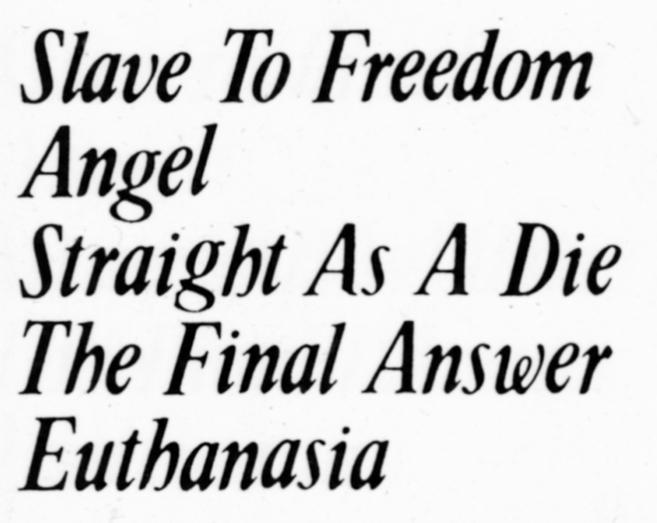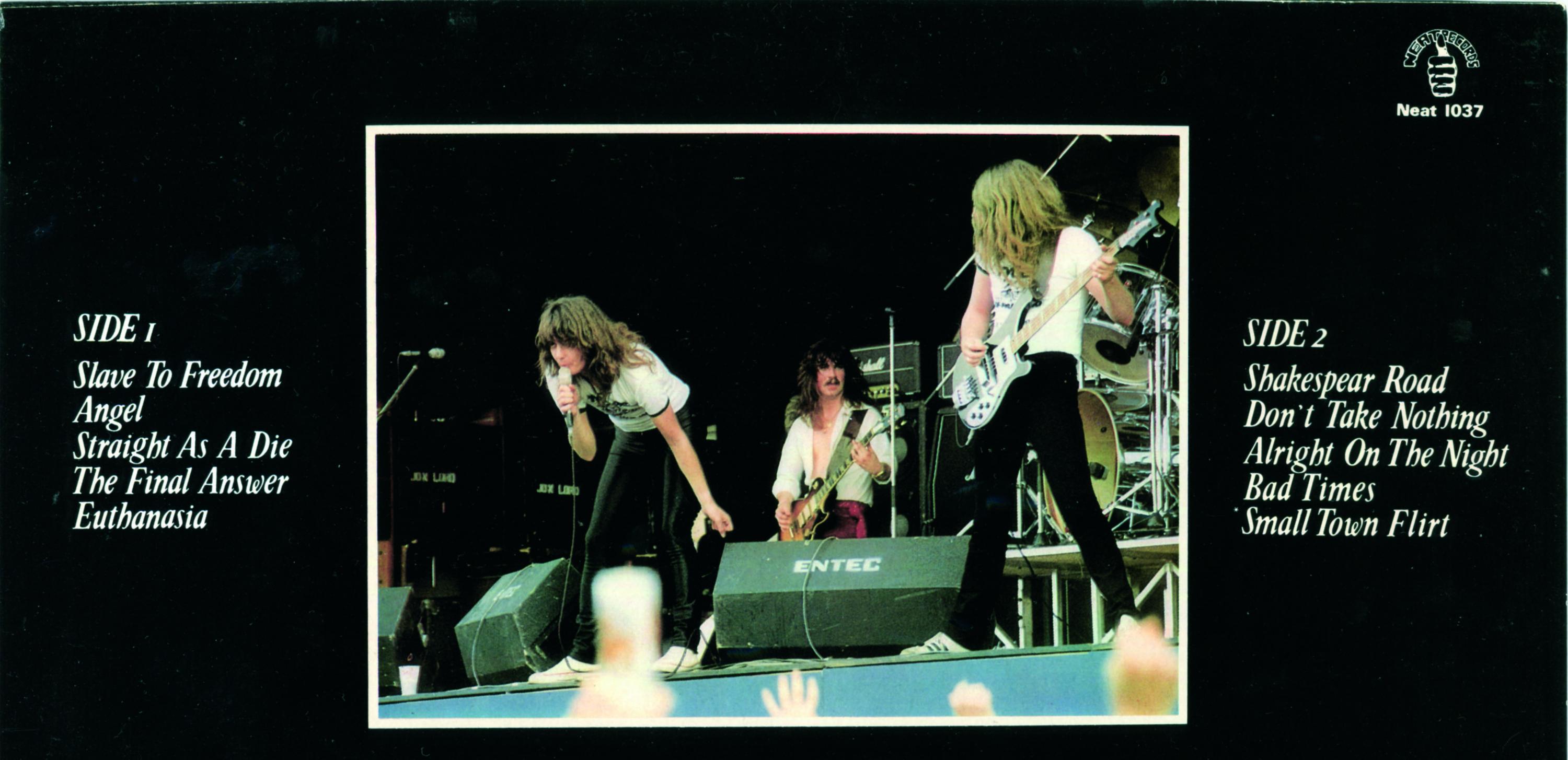
Suche 2 Schriften für ein Vinyl-Rerelease (Tygers of Pan Tang)
Für ein offizielles Vinylrelease suche ich 2 Fonts. Das Original erschien 1986.
Ich dachte, es wären die Baskerville und die Zapf Chancery. Leider sind sie nur ähnlich.
konkrete Angaben zum Originalrelease:
Titel: First Kill
Band: Tygers of Pan Tang
Jahr: 1986
Label: Neat Records (Europe)
die Anhänge sind Scans des Originalreleases
"Tygers" ist aus der Zapf Chancery.
y und g sind in der Chancery auch nicht original … oder aus dem Kursivschnitt geradegestellt o.ä.
Ok - vielen Dank. Das mit kursiv geradestellen bei der Chancery hab ich probiert. Das passt auch. Bei der anderen muss ich mal probieren.